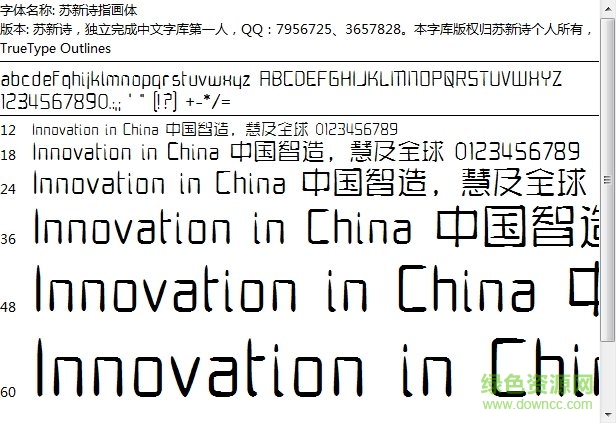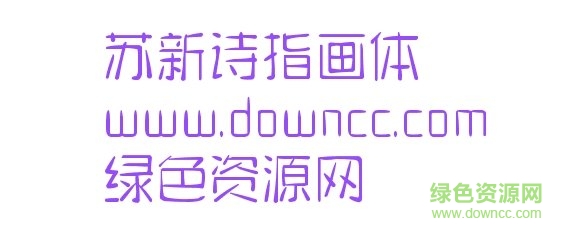
蘇新詩(shī)指畫(huà)體字體
蘇新詩(shī)指畫(huà)體是一款造型端正、筆畫(huà)清晰的手寫(xiě)字體,結(jié)合了圓潤(rùn)和棱角的特色,讓文字更顯得生動(dòng)大氣起來(lái),藝術(shù)效果十分不錯(cuò),來(lái)綠色資源網(wǎng)即可免費(fèi)體驗(yàn)!
蘇新詩(shī)指畫(huà)體字體特色
蘇新詩(shī)指畫(huà)體,將筆畫(huà)處理的即圓潤(rùn)又尖銳,橫平豎直間造型類似于手指,給人趣味童真體驗(yàn),是蘇新詩(shī)最新推出的藝術(shù)字體,可以廣泛運(yùn)用在藝術(shù)設(shè)計(jì)、平面設(shè)計(jì)、海報(bào)設(shè)計(jì)等諸多場(chǎng)合。